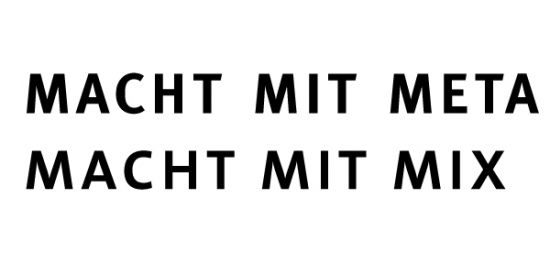
Meta vs The Mix
Weiß jemand mehr über diese 2 verdammt ähnlichen Schriften.
Meta von Spiekermann, irgendwann anfang der 90er als
Hausschrift für die Post gedacht, dann nach ablehnung
kommerziell weiterentwickelt.
Was aber mit The Mix, kein Plan. Wann, Wer, Warum? Wie zwei Z'willinge. Unterschiede in den Details und Formführung aber generell
The Mix (Thesis Mix) ist eine Schrift von Luc(as) de Groot, und Teil der Sippe Thesis (zusammen mit Sans, Serif und Antiqua).
Mit der Meta hat sie eigentlich nur gemein, dass beide »Serifenlose« (kommt natürlich auf die Thesis-Variante an) mit Renaissance-Charakter sind.
Im Detail sind da aber große Unterschiede. Meta läuft schmaler, hat gewinkelte Anstriche, ein völlig anderes g, ..., ...
Ich würde die Thesis eher ins Frutiger-Eck stellen als ins Meta-Eck.
die beiden haben doch völlig unterschiedliche geometrien. in versal sehen fast alle sans serif nebeneinandergestellt ähnlich aus. das liegt in der natur der dinge.
caecillia und the serif unterscheiden sich aber schon einigermassen. da gibts schlimmere beispiele ;)
Das hat doch Max Caflisch »entdeckt«, dass sich die recht ähnlich sind, nicht?
Schüler/Lehrer eben...
Ich finde diese »Mama, da hat mir jemand was abgeguggt!«-Debatten ziemlich peinlich. Schließlich hat jeder bei seiner Arbeit Vorbilder und wenn ein Designer sich Anleihen beim Entwurf eines Kollegen holt, sollte jener das als Kompliment und nicht Affront betrachten (ich glaub David Gahan hat das auch mal in Bezug auf Samples die viele andere Musiker von Depeche Mode entlehnt haben gesagt; recht hater!). Und von Plagiaten kann man ja wohl weder bei der Thesis noch bei der Meta sprechen.
"dave" gahan. soviel zeit muss sein. ;)
Ach Jungs! Das ist echt hart mit euch. 8)